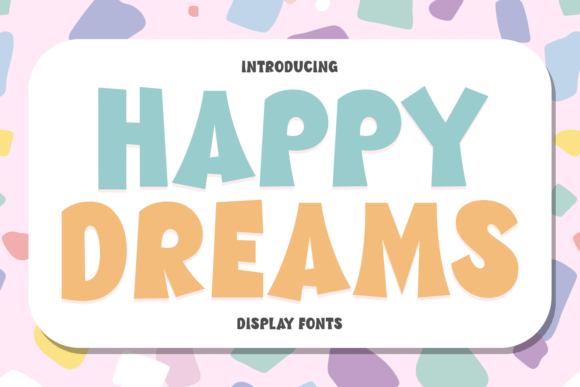
Happy Dreams
إذا كنت تبحث عن أصول عالية الجودة مثل Happy Dreams، فإن هذه الحزمة المميزة هي خيار رائع لمشاريعك الإبداعية.
تم تصميمه بدقة، ويوفر Happy Dreams متجهات نظيفة وطباعة سلسة وترخيصًا تجاريًا لراحة بالك.
سواء كنت تقوم بإنشاء منتجات الطباعة عند الطلب أو دعوات الزفاف أو رسومات وسائل التواصل الاجتماعي، فإن Happy Dreams هو الخيار المثالي.